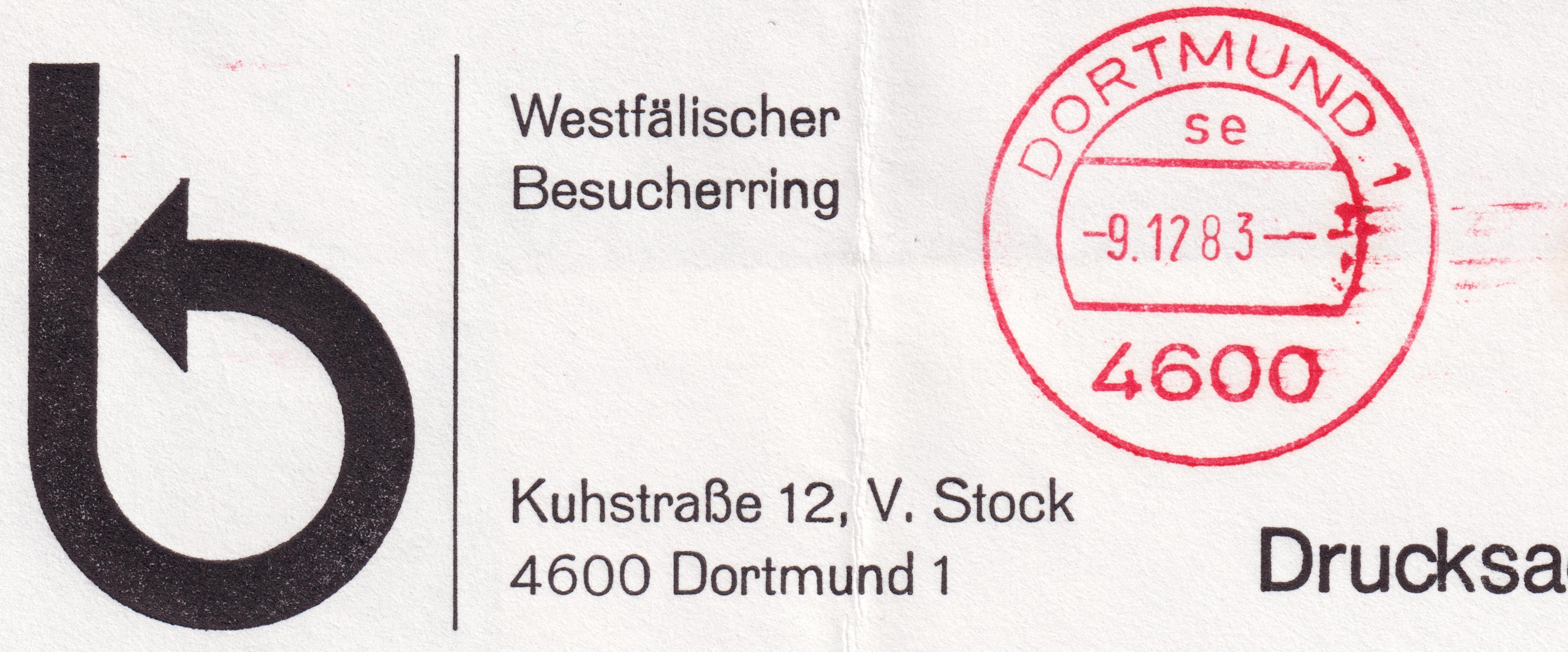
Serifenlose Schrift des Westfälischen Besucherrings
Auf einem alten Briefumschlag aus dem Jahre '83 entdeckte ich eine altmodische Groteske.
Könnte es sich hier um die magere Aurora handeln?
Wurde sie je digitalisiert?